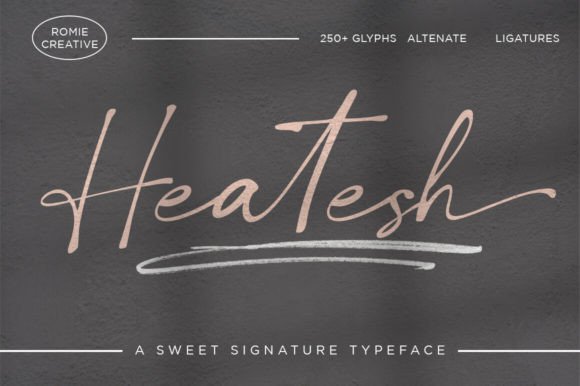
Heatesh Script
Om du letar efter högkvalitativa tillgångar som Heatesh Script, är detta premiumpaket ett fantastiskt val för dina kreativa projekt.
Tillverkad med precision, ger Heatesh Script rena vektorer, smidig typografi och en kommersiell licens för sinnesfrid.
Oavsett om du skapar POD-produkter (Print on Demand), bröllopsinbjudningar eller grafik för sociala medier, är Heatesh Script ett perfekt val.